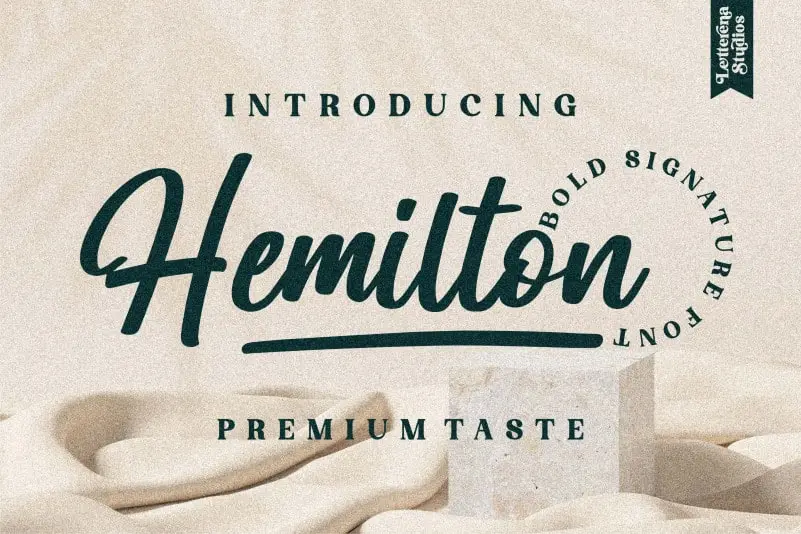
Hemilton Script Font – Download Grátis
A Hemilton Script Font é uma fonte feita à mão que transmite uma sensação mágica e encantadora. Essa fonte script é versátil e pode ser usada para um vasto número de aplicações, desde cartões de cumprimentos até headlines, garantindo sempre que seu próximo projeto tenha um ar romântico. Ideal tanto para designers gráficos quanto para aqueles que desejam adicionar um toque delicado a seus projetos, essa fonte não decepciona. Sua elegância e sofisticação se combinam com uma personalidade vibrante, tornando-a perfeita para uso em diversos ambientes digitais e impressos. Experimentar Hemilton Script é invitar o charme do papel à sua disposição.